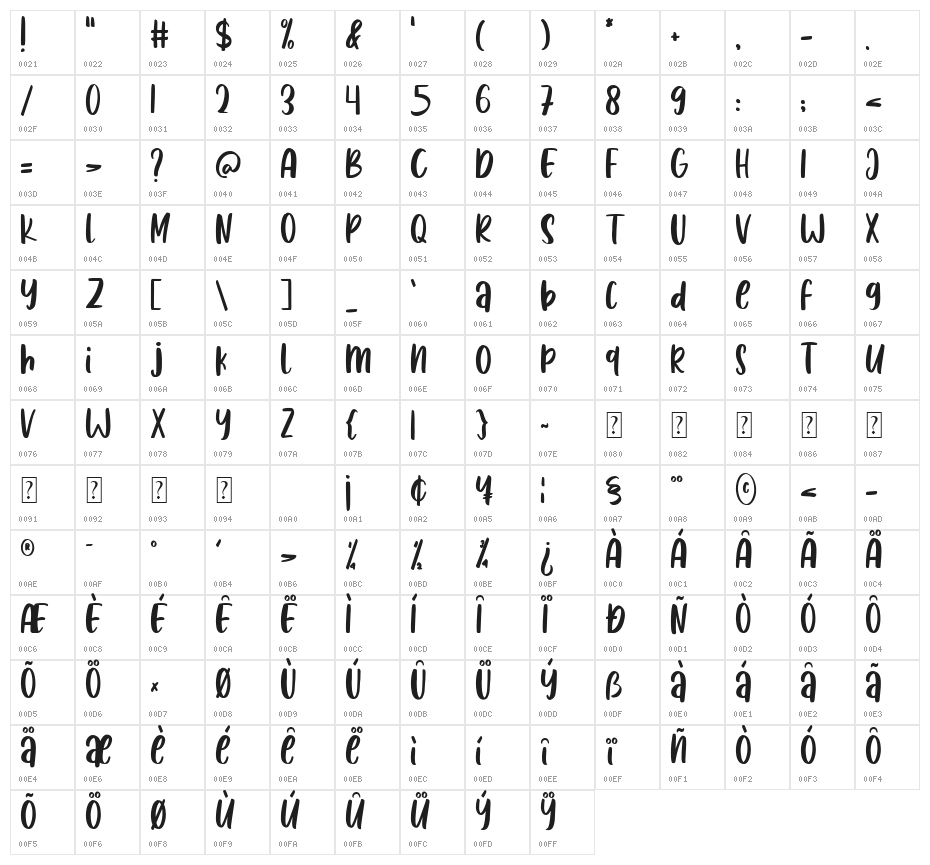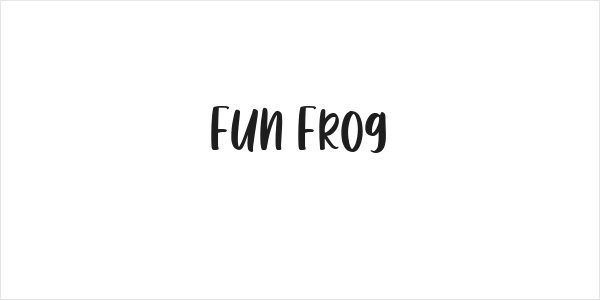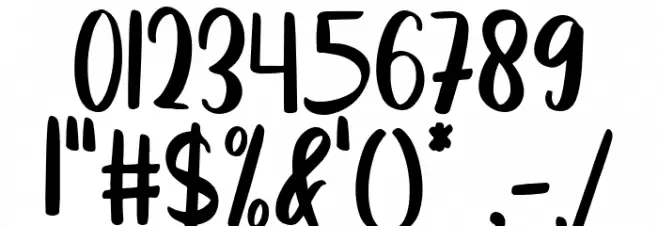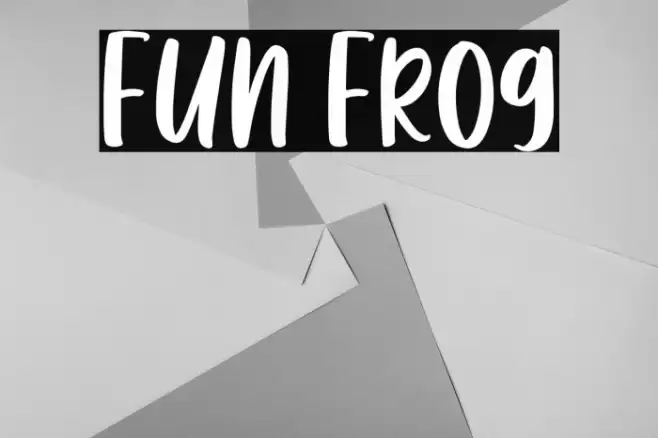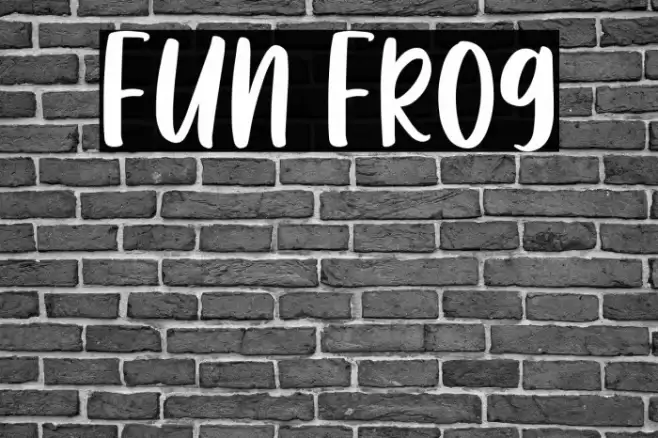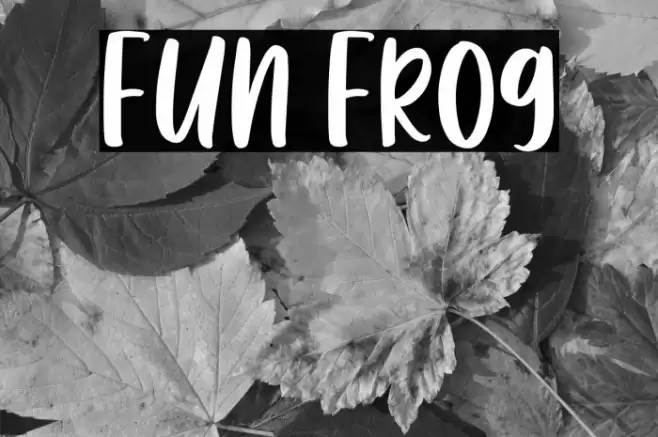
Fun Frog Font
| Gesamtstil | Playful |
| Vorgeschlagene Projekte | Ideal for children's books, playful branding, creative posters, and informal invitations. |